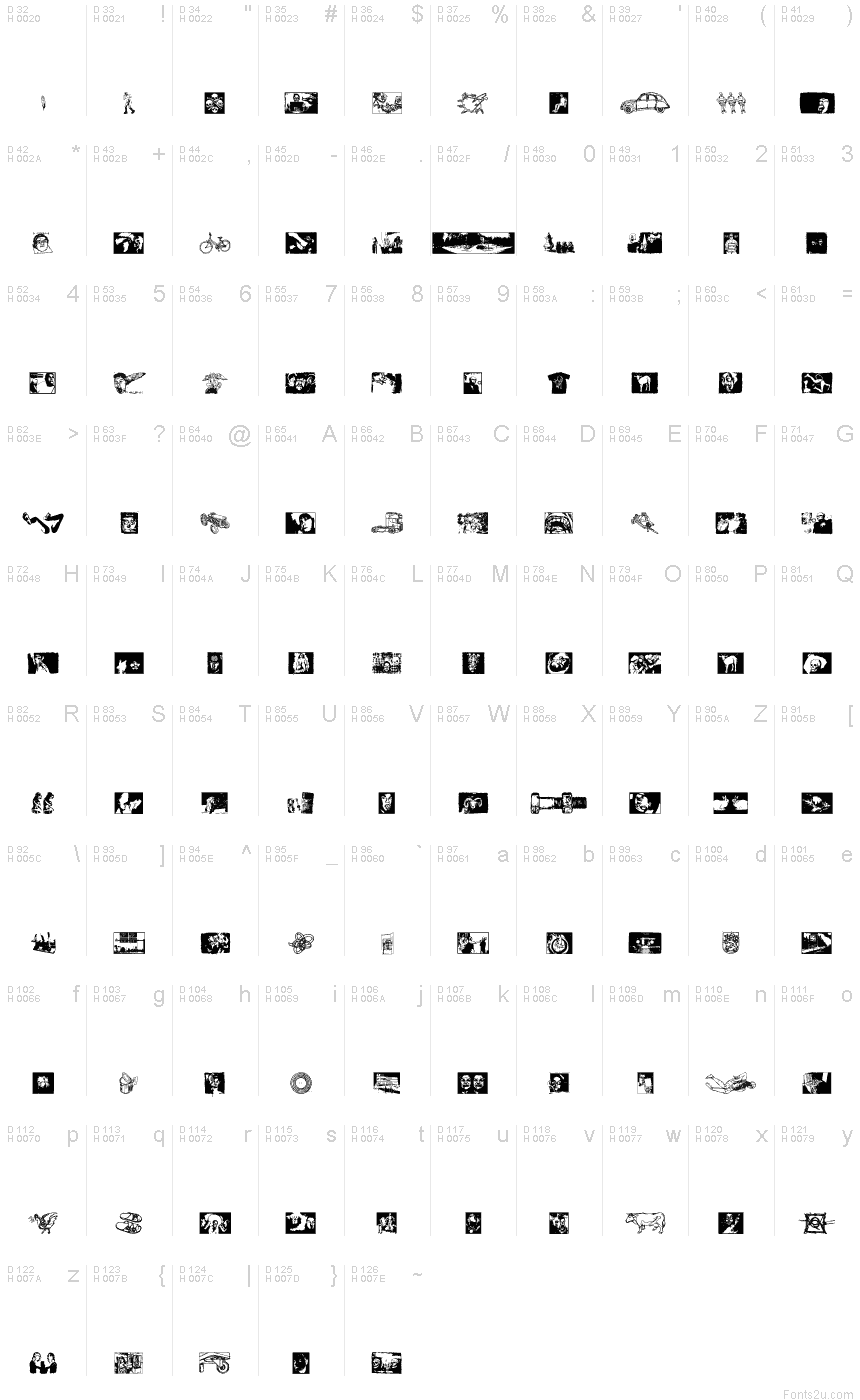
3-2-1-jungbats od Junkohanhero to darmowy grunge’owy font typu dingbat. Każdy glif przypomina fotokopię wyrwaną z podziemnego fanzinu: surowe czarno-białe ujęcia ludzi, poszarpane krawędzie, chropowate tekstury i filmowe kadrowanie. Zamiast grzecznych ikon otrzymujesz niepokojące winiety – twarze, dłonie, znaki – które wskakują w projekty niczym gotowe panele, nadając pracy natychmiastowy, surowy klimat fotokopii z podłogi klubu.
3-2-1-jungbats pozwala tworzyć plakaty, okładki albumów, zinów, ulotki horrorów, eksperymentalne komiksy i wyrazistą grafikę do social mediów bez dotykania aparatu. Gęste czarne bloki szybko kotwiczą kompozycje, dzięki czemu pojedynczy glif może stać się głównym elementem graficznym lub powtarzalnym wzorem. Ten darmowy font świetnie komponuje się z czystym bezszeryfowym krojem typu neo-groteska w mniejszym rozmiarze – dzięki temu grunge’owe ilustracje przejmują cały dramatyzm, podczas gdy tekst pozostaje ostry i czytelny.